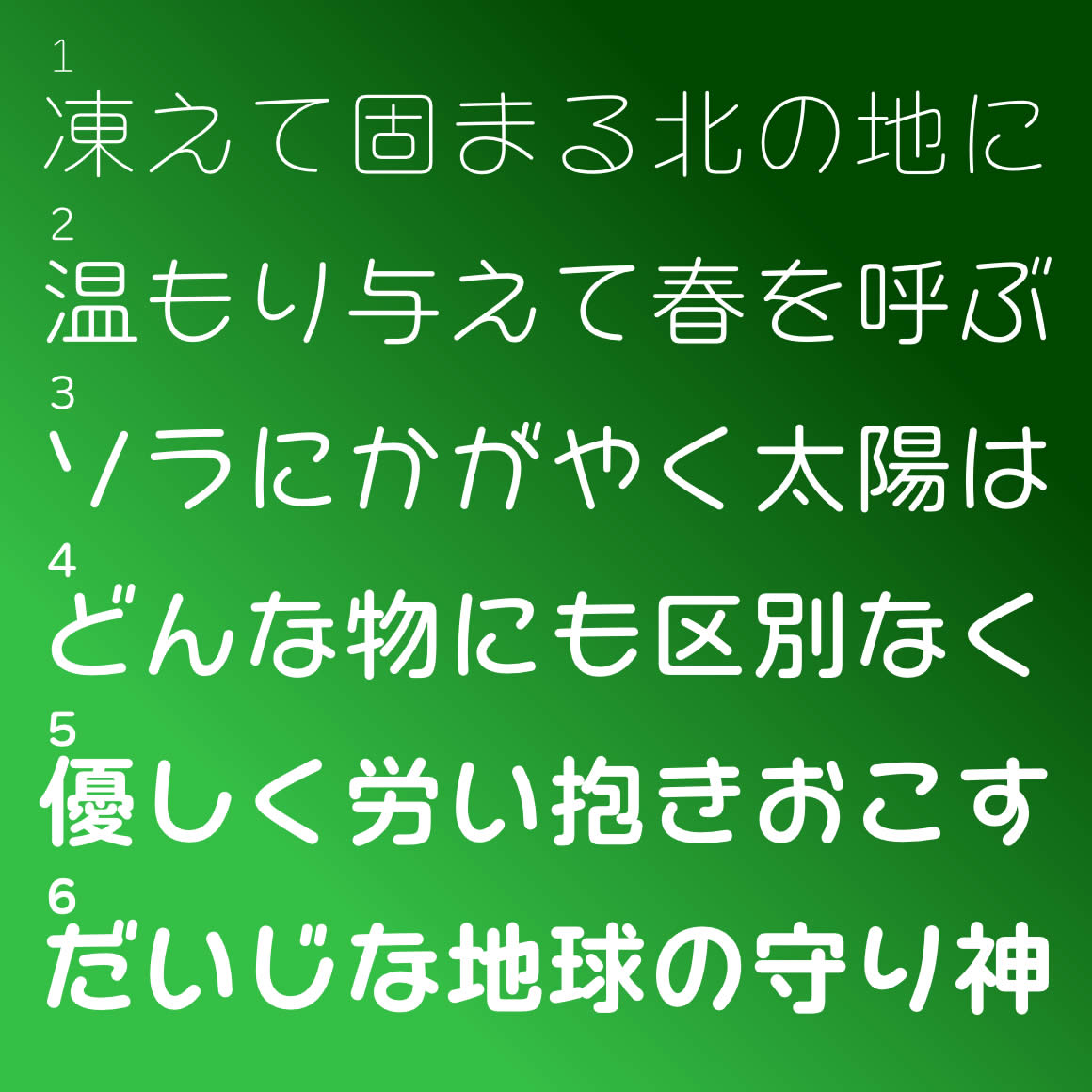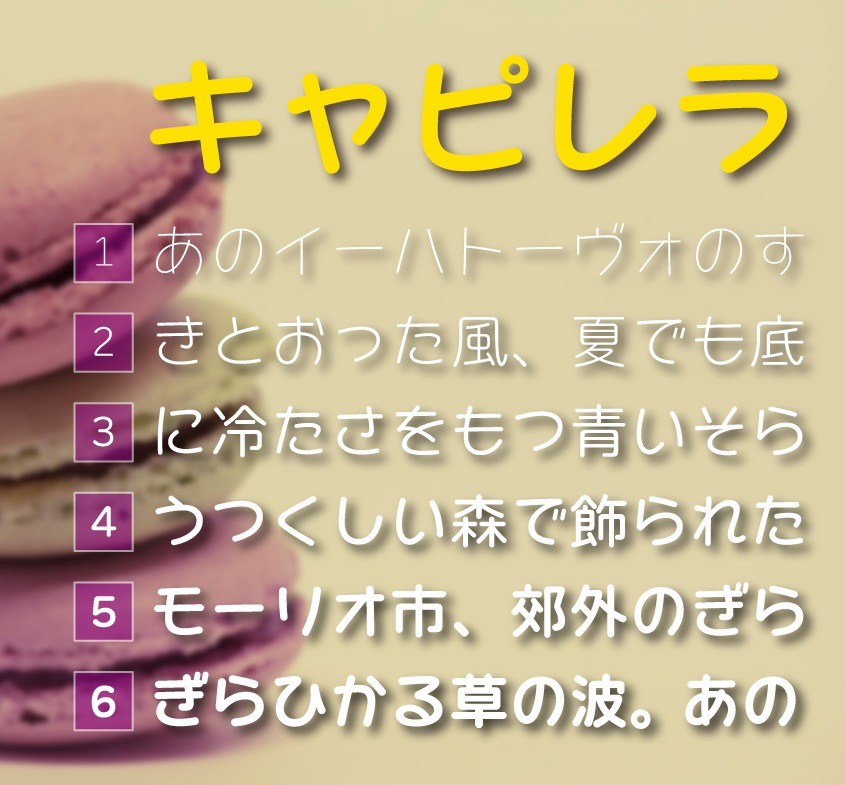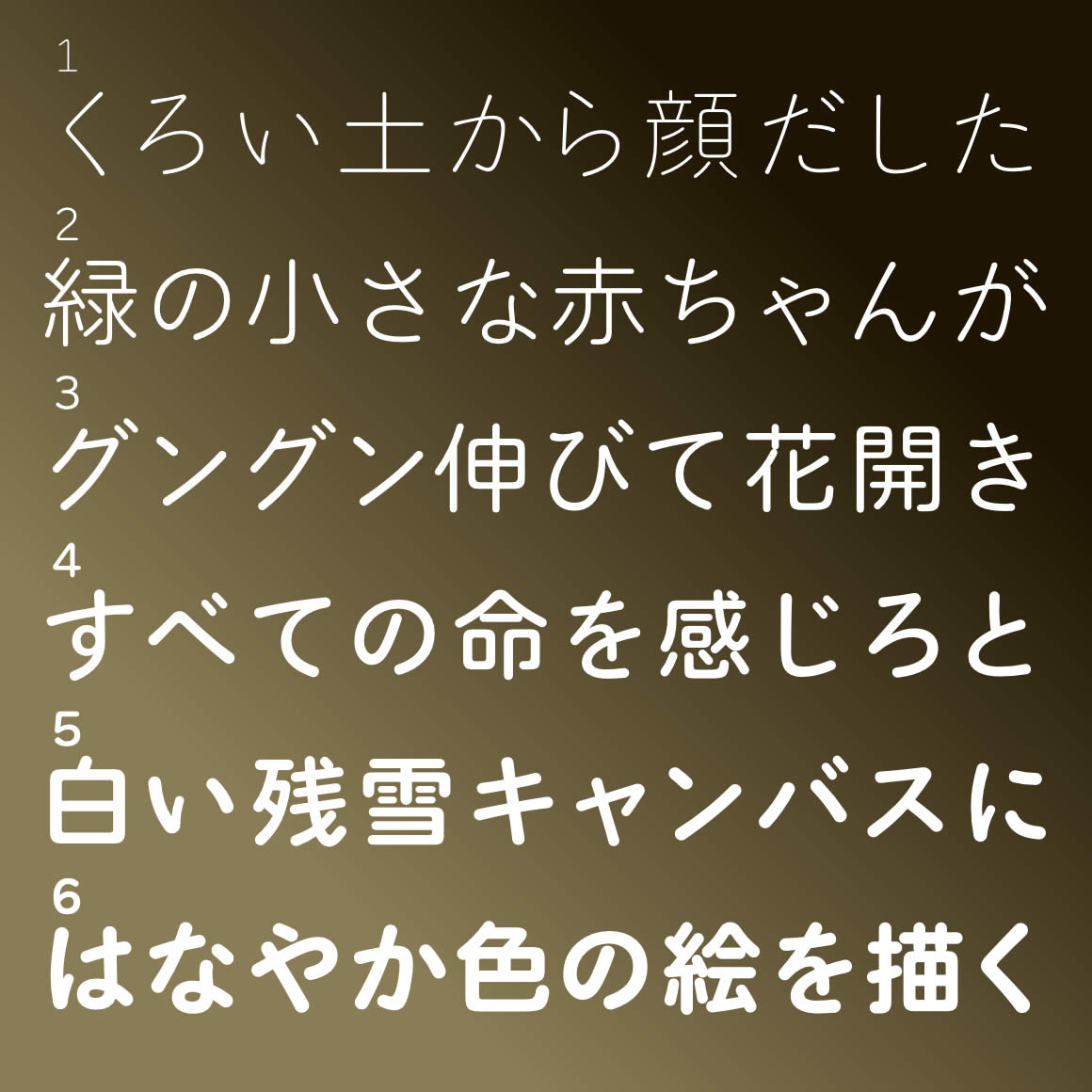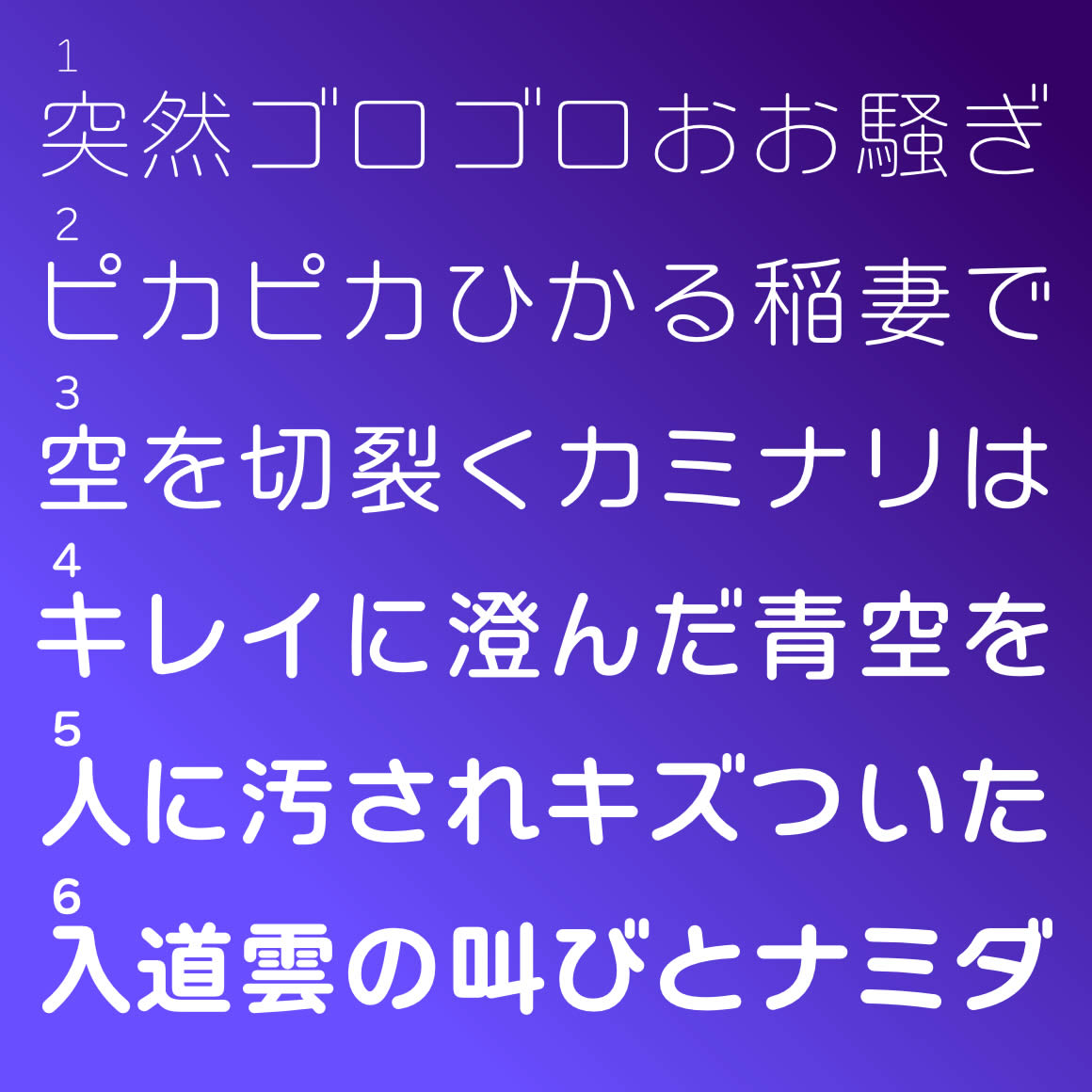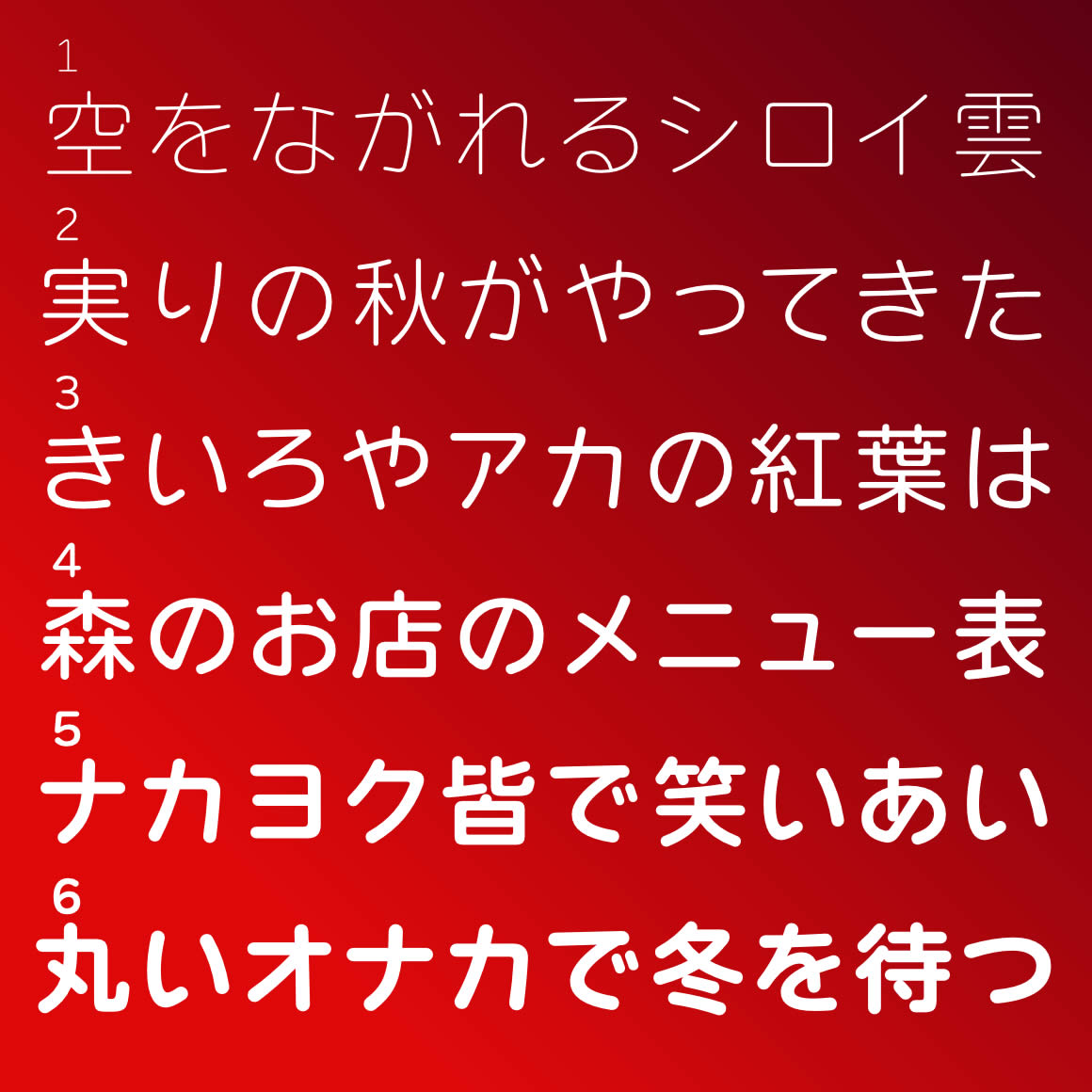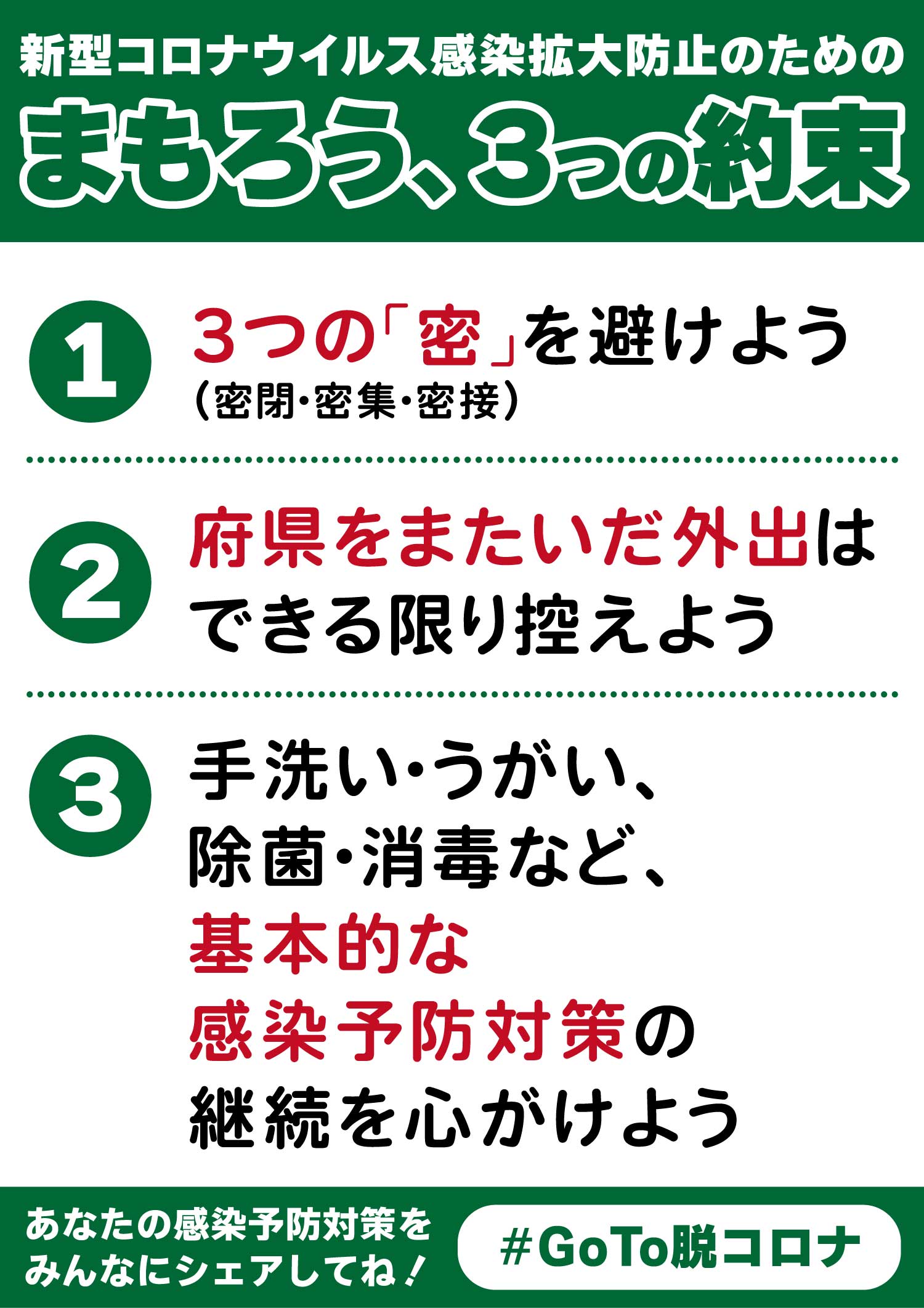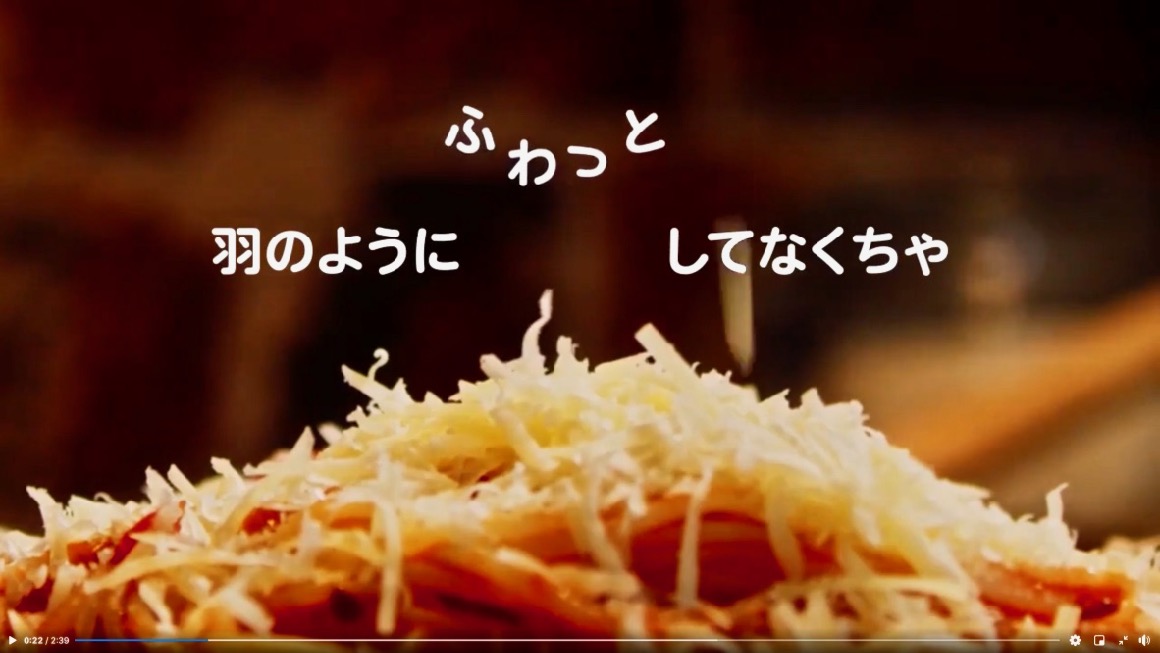
アニメ「RPG不動産」の劇中で「わんぱくレラ」が使われていました。
右から3列目までがわんぱくレラ、一番左の墨東も「墨東ルイカ」かと思います(たぶんAdobe Fonts)。
左側の「可愛くない」紛れもなく正真正銘の墨東ルイカですね。
墨東レラ、ファミマのキャンペーン。
墨東レラの使用例。
SNSオピニオン紙 日刊ココちゃん通信の2月更新ヘッダーです。
墨東レラ
ニタラゴレラ を使用しています。
今日の「ココちゃん通信」第165号の紙面です。
トップ横見出しは ニタラゴラレ その下はえれがんと平成明朝
縦見出し レラ あられ
リード キャピレラ
写真説明 キャピレラ
横中央見出し えれがんと平成明朝
今日の「ココちゃん通信」第165号紙面下面です。
縦見出し わんぱくレラ 中見出し ニタラゴレラ
囲み 本文 わんぱくレラ
レラ
えれがんと平成明朝 キャパニト
タイプラボさんのフォントは作りがプロ仕様なので新聞での利用は抜群です。今日も多くのフォントを使わせてもらいました。有難うございます。
最近は縦組みが珍しいので、新聞に使われた例は貴重です。
ブログのヘッダーのサブ的な意味でのもの。月替わりでその月にあったものになっています。
上は あられ 使用です。
うめ吉のブログ「ココちゃん家族だワン」のヘッダーです。
わんぱくレラ ニタラゴレラを使用しています。
「ココちゃん通信」 今日12月17日発行 第163号です。
主見出し わんぱくレラ その下は えれがんと平成明朝
縦見出し ニタラゴレラ 同じくニタラゴレラ
リード レラ
中央見出しは キャピレラ
写真説明 キャピレラ
下段縦 レラ
囲み 本文 わんぱくレラ 下はセプテンバー あられ わんぱくレラ
縦見出し レラ
囲み記事 本文 わんぱくレラ
下部分 セプテンバー
あられ わんぱくレラ
今日のではありませんが、ゴシック系のルイカで「、」がある時はえれがんと平成明朝に置き換えています。新聞見出しで「、」は明朝体にしていることに順じた対応です。それと、この新聞でえれがんと平成明朝を使う時はかなが入らない漢字だけの見出しを考えてつけています。社会問題が主の新聞ですから、ロマン書体のえれがんとの「くるりん」では場違いになるので。
ココちゃん通信 第162号  大阪のうめ吉  2021年12月16日(木) 5:53  Mail
SNSオピニオン紙 日刊「ココちゃん通信」 第162号
横見出しトップ ニタラゴレラ その下 あられ
縦見出し ニタラゴレラ セプテンバー
リード レラ
中央 ルイカ 写真説明 キャピレラ
ココちゃん通信 第162号下段  大阪のうめ吉  2021年12月16日(木) 5:58  Mail [修正]
下段です。
縦見出し ニタラゴルイカ
囲み記事 セプテンバー あられ わんぱくレラ
さとうゆたか  2021年12月16日(木) 9:03 [修正]
大阪のうめ吉さん、投稿ありがとうございます。
まだまだ、レラ系の使用例が少ないので、貴重です〜。